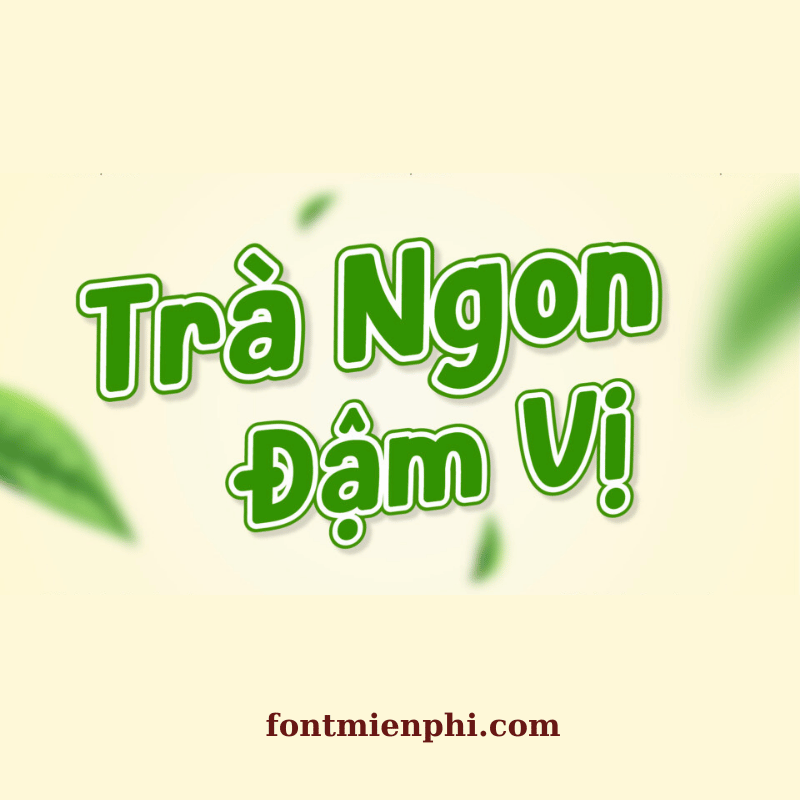
Font Việt hóa 1FTV VIP Milk Kids
Font Việt hóa 1FTV VIP Milk Kids  – Nét Chữ Ngộ Nghĩnh Cho Bé Yêu
Giới Thiệu
Font Việt hóa 1FTV VIP Milk Kids là bộ font chữ độc đáo, thiết kế dành riêng cho trẻ em với phong cách ngộ nghĩnh, đáng yêu. Được Việt hóa chuẩn chỉnh, font chữ này phù hợp cho các dự án thiết kế đồ họa, in ấn sách truyện, giáo cụ học tập hay sáng tạo nội dung dành cho thiếu nhi. Với đường nét mềm mại, bắt mắt, Milk Kids giúp thu hút sự chú ý của các bé và tạo điểm nhấn ấn tượng.
Đặc Điểm Nổi Bật
• Thiết kế sinh động: Nét chữ tròn trịa, ngộ nghĩnh, phù hợp với các ấn phẩm dành cho trẻ em.
• Chuẩn Việt hóa: Hỗ trợ đầy đủ dấu tiếng Việt, dễ dàng sử dụng trong mọi phần mềm thiết kế.
• Đa dạng ứng dụng: Dùng làm font chữ đẹp cho poster, thiệp mời, tài liệu giáo dục, truyện tranh, logo cửa hàng đồ chơi…
Lý Do Chọn Font VIP Milk Kids
Font 1FTV VIP Milk Kids không chỉ đẹp mà còn tối ưu cho in ấn và hiển thị kỹ thuật số. Phong cách tươi vui của font giúp truyền tải thông điệp một cách gần gũi, kích thích sự sáng tạo của trẻ nhỏ.
Kết Luận